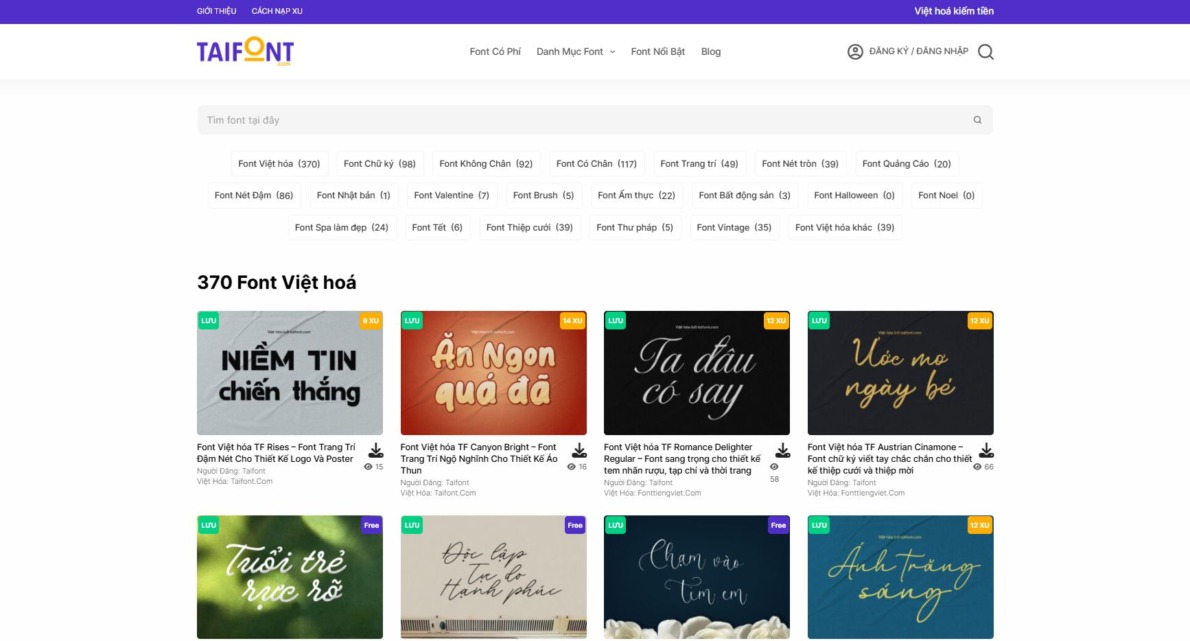
500+ Font Việt Hóa Đẹp Dành Cho Thiết Kế Sáng Tạo & Thương Hiệu
500+ Font Việt Hóa Đẹp – Kho Tài Nguyên Vàng Cho Designer Việt
Vì sao nên chọn font Việt hóa?
Khác với font quốc tế thông thường, font Việt hóa đã được tùy chỉnh để hiển thị đầy đủ dấu tiếng Việt – từ á, ư, ơ cho đến chữ in hoa có dấu. Điều này đảm bảo tính thẩm mỹ, chuyên nghiệp và rõ ràng cho mọi dự án thiết kế, từ thương hiệu đến truyền thông.
Ưu điểm nổi bật của font tại TaiFont:
• Chất lượng cao, không lỗi dấu
• Phân loại rõ ràng theo phong cách: script, sans, serif, display, retro, vintage, …
• Hỗ trợ tiếng Việt đầy đủ – thích hợp làm tiêu đề, logo, typography
Một số danh mục nổi bật tại TaiFont:
• Font viết tay (handwriting)
• Font hiện đại – sans serif
• Font vintage – retro
• Font cho thiết kế ẩm thực, mỹ phẩm, thời trang
• Font phong cách Nhật, Hàn, Trung độc đáo